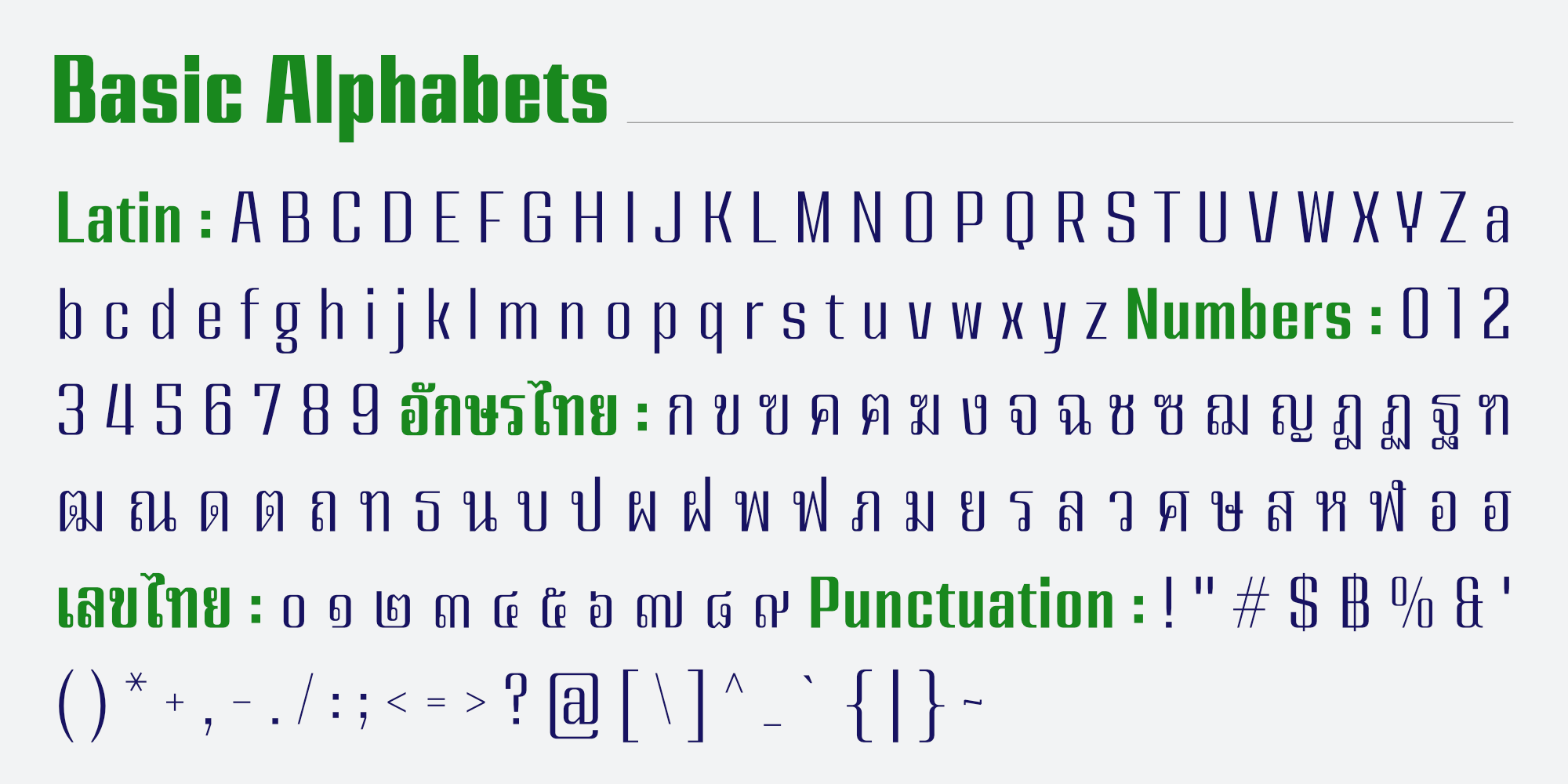
หน้าหนึ่ง | Nanueng
ชื่อฟอนต์ : หน้าหนึ่ง | Nanueng
ฟอนต์sหน้าหนึ่ง เป็นอักษรแบบแซนเซอริฟที่แบบอักษรโดยรวมมีความเป็นสีเหลี่ยม  ซึ่งแบบอักษรจากหนังสือพิมพ์เป็นแรงบันดาลใจ ดูแข็งแกร่ง มีความเป็นเครื่องกล เครื่องจัก ทันสมัย เหมาะสำหรับการใช้พาดหัว รองพาดหัว มีทั้งหมด 9 น้ำหนักและตัวเอียงของแต่ละน้ำหนักรวมทั้งหมดมี 18 สไตล์ และมีฟีเจอร์อื่น ๆ เช่น Stylistic Set 01 และฟีเจอร์อื่น ๆ พร้อมให้คุณได้เลือกใช้งาน รองรับหลากหลายภาษา
Nanueng is a sans serif display typeface with square shape base. Inspiration from typeface on the Thai newspapers. Look strong, machine and modern feel. Suitable for headline, sub-headline Comes with 9 weights and italics of each weight total 18 styles, and there are features such as Stylistic Set 01 and many features available for you. Support multi-languages.
Creator : อานุภาพ ใจชำนาญ (Anupap Jaichumnan)